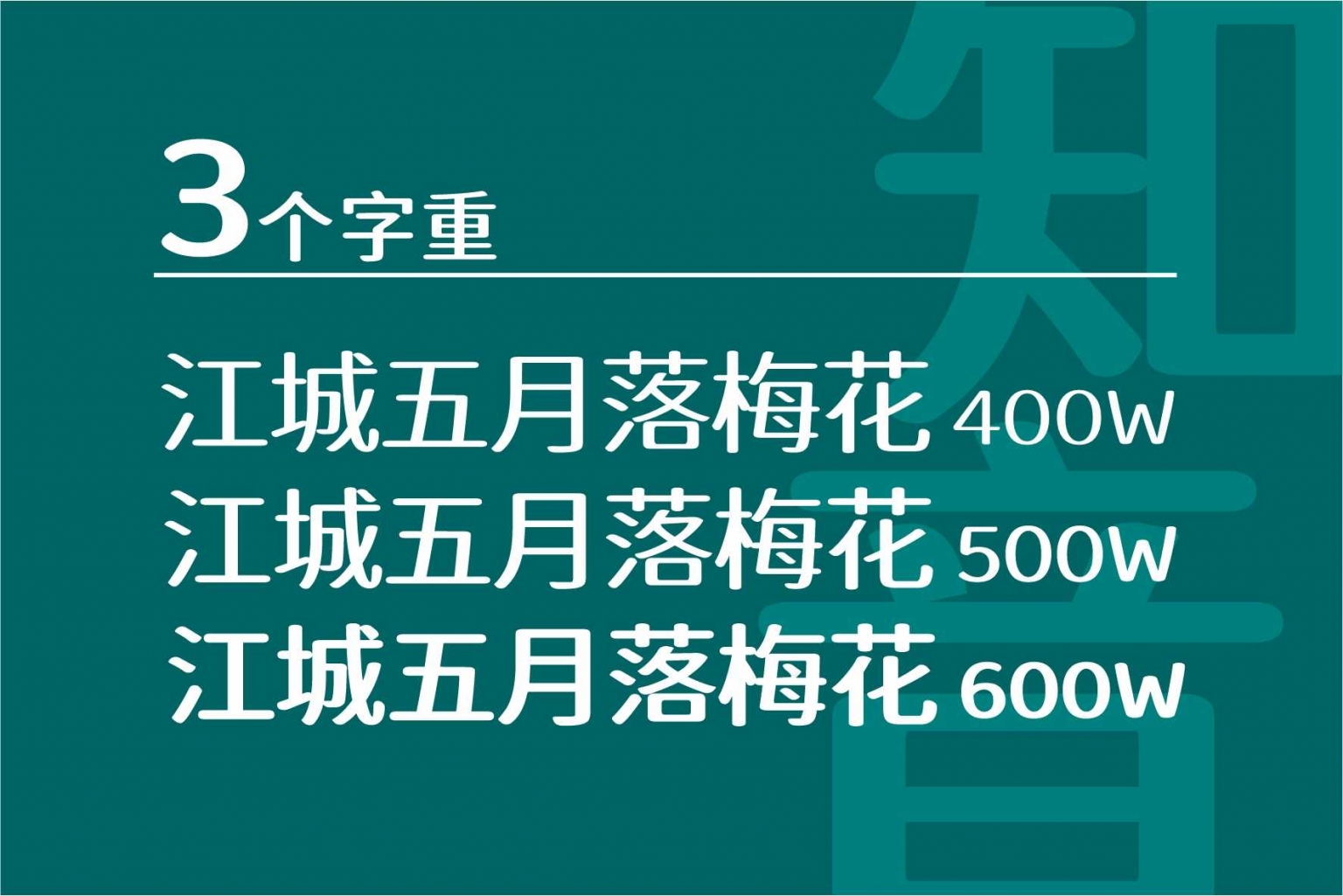
江城知音体是基于同系列字体江城圆体改造而成的一款免费可商用字体,作者刘鹏(微博 @设裂星辰)将原字体的横向笔画进行减细处理,纵向笔画进行增粗处理,就得到了现在的江城知音体。
江城知音体包含 Regular (400W)、Medium (500W)、Bold (600W) 3 个字重,支持简体与繁体中文以及附加的英文字体和阿拉伯数字等字符集。可以适用各种用字场景,比如品牌 LOGO、海报标题、宣传物料、广告包装等。
- 修复网友反馈的字形问题,减少毛刺、字宽、字距不均等现象。
- 西文字母及数字选用 Baloo2 字体改造,提升整体协调性。
- 优化字符集,确保简体与繁体中文的完整性。
- 调整部分笔画细节,提升字体美观度。